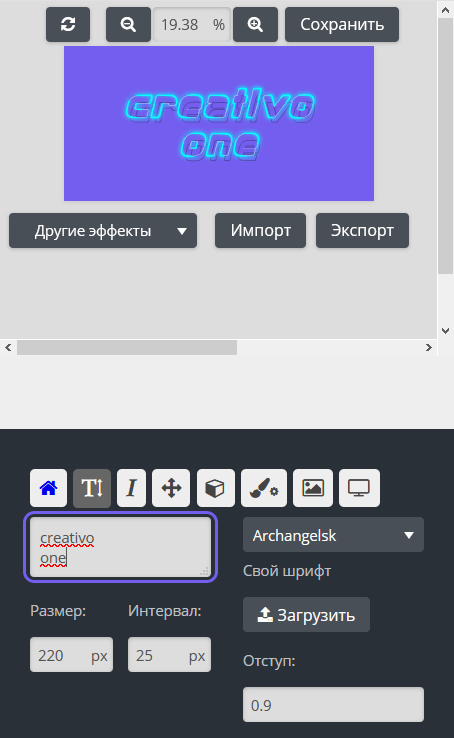
Красивый шрифт онлайн без программ
Как добавить любому шрифту красивый эффект и оригинальный стиль, без программ используя только телефон. Отличный вариант для создания визуального контента, обложки, перевью, шапки и рекламы. Онлайн приложении надписей logotextom, за пару кликов можно добавить шрифтам разные эффекты например: 3д, неон, глитч, киберпанк и другие эффекты.
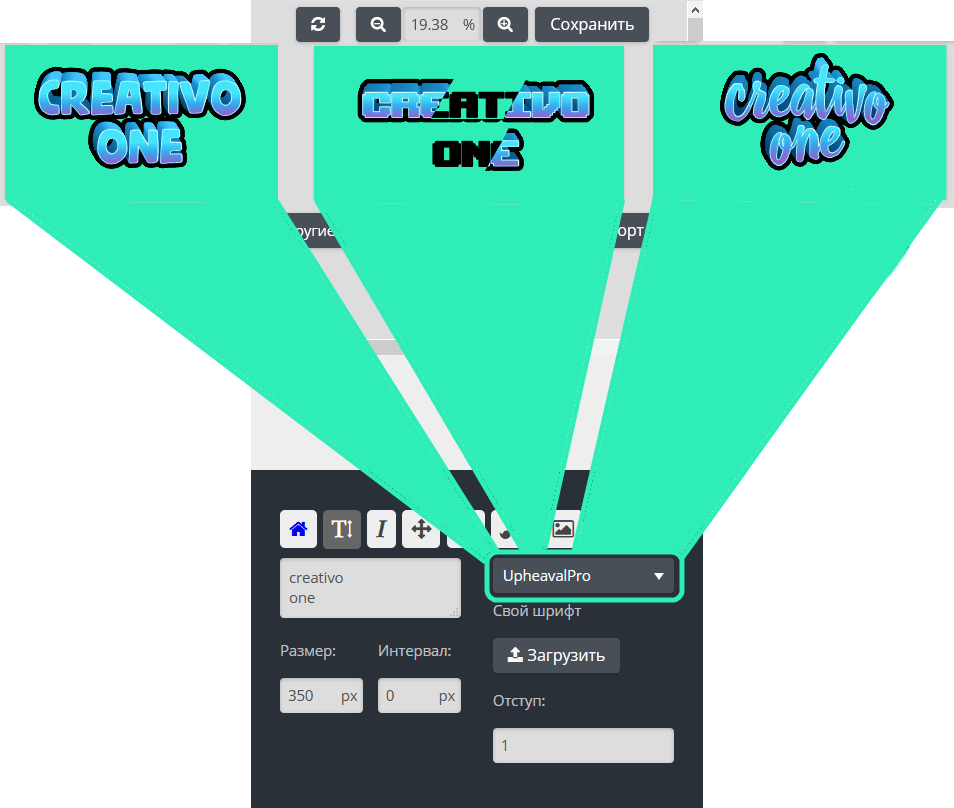
Красивый шрифт онлайн без программ
Навигация и управление конструктором простая и понятная, для добавления эффекта шрифту вам нужно выбрать готовый стиль, из списка предустановленных или создать свой оригинальный эффект.
1. Выбираем эффект
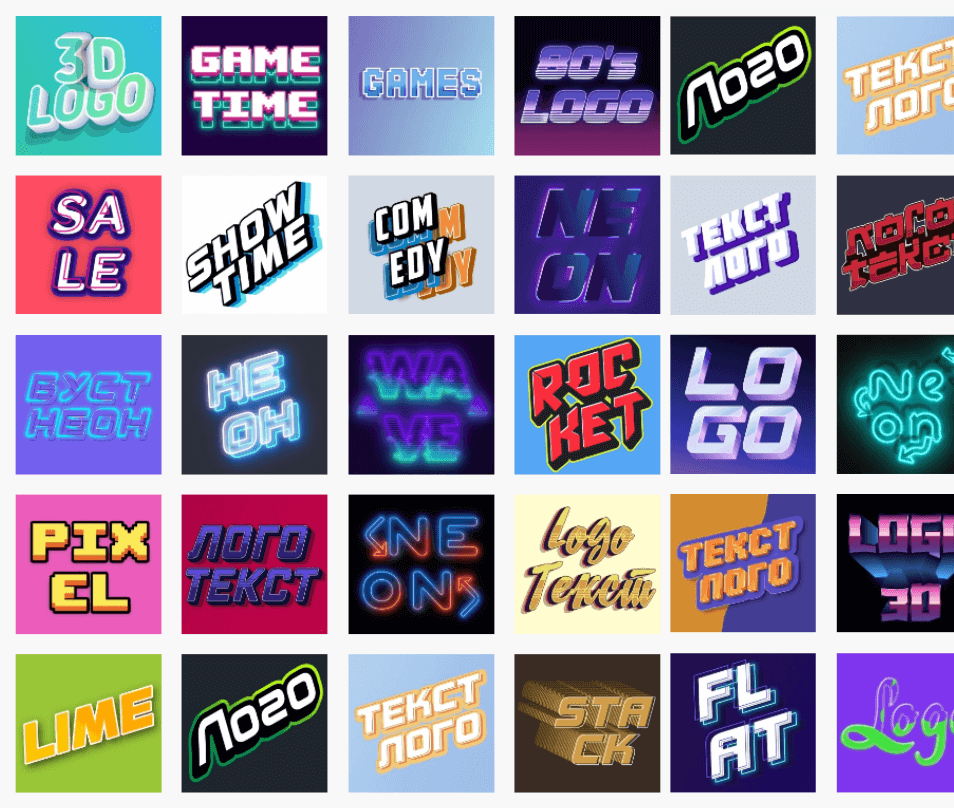
Красивый шрифт онлайн без программ
2. Ввести свой текст
Красивый шрифт онлайн без программ
3. Выбирать или загрузить свой шрифт.
Красивый шрифт онлайн без программ
4. Сохранить
Красивый шрифт онлайн без программ